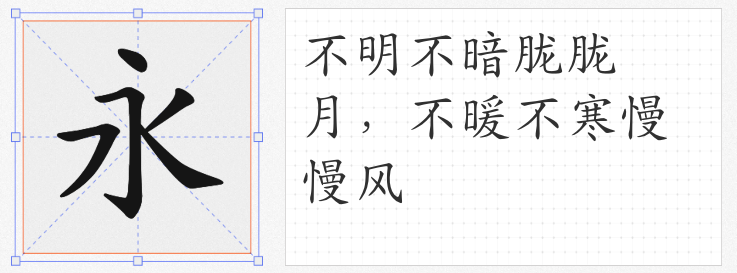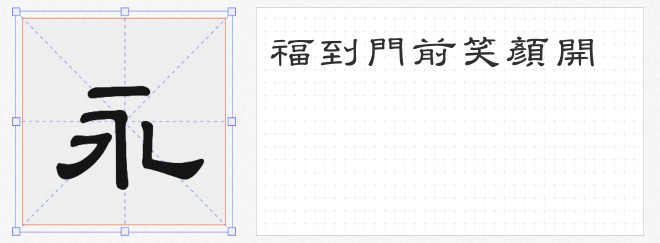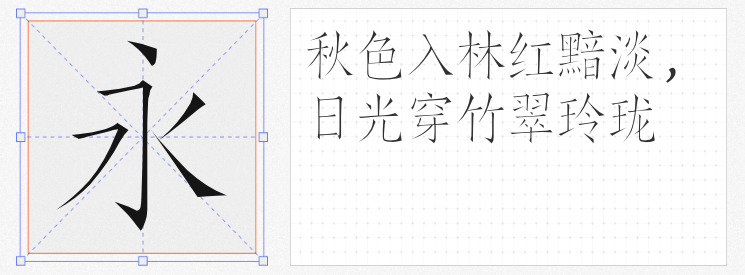
在数字化设计浪潮中,兼具文化底蕴与实用性的书法字体成为设计师的刚需。本文精选四款免费商用书法字体,涵盖仿宋、楷书、草书、隶书四大经典书体,为品牌包装、文化海报、影视字幕等场景提供合规且富有表现力的解决方案。
作为AI生成的仿宋字体,天空仿宋以“聚珍仿宋体”为蓝本,通过机器学习重构了1915年丁善之、丁辅之兄弟创制的经典笔型。其横画保持15°上扬斜度,折笔处保留“燕尾”特征,但笔画粗细误差控制在±0.03mm以内,解决了传统仿宋体因手工雕刻导致的笔画不均问题。适用于古籍排版、学术报告等需要严谨与雅致并存的场景。
由文鼎科技2001年捐赠给开源社区的这款字体,是Linux系统首款高质量楷体。其字形结构取法颜真卿《多宝塔碑》,中宫收紧而四梢舒展,横画起笔的蚕头与捺画出锋的雁尾形成呼应。该字体包含6763个简体汉字,覆盖GB2312标准,在WPS、LibreOffice等开源软件中表现稳定,特别适合教育出版、公益宣传等需要权威性的场景。
这款由贴吧大神mikhailcai基于孙过庭《书谱》开发的狂草字体,通过算法将17000个繁体汉字规范化为统一风格。其笔画连绵如“屋漏痕”,字与字之间保留20%的飞白空间,形成独特的视觉韵律。网友“落霞孤鹜”开发的简入繁出版本,通过字形映射技术实现简体输入自动转换繁体输出,解决了草书繁简转换的难题,适用于文化创意产品、国风游戏等需要强烈艺术张力的场景。
依据台湾《教育部隶书母稿》制作的这款字体,收录4808个标准字形,笔画平直如“折钗股”,横画末端的波磔幅度严格控制在字高的1/8。作为台湾中小学教材、公文的法定用字,其字形规范性与文鼎楷体形成互补,特别适合两岸文化交流项目、古籍整理等需要兼顾两岸用字习惯的场景。